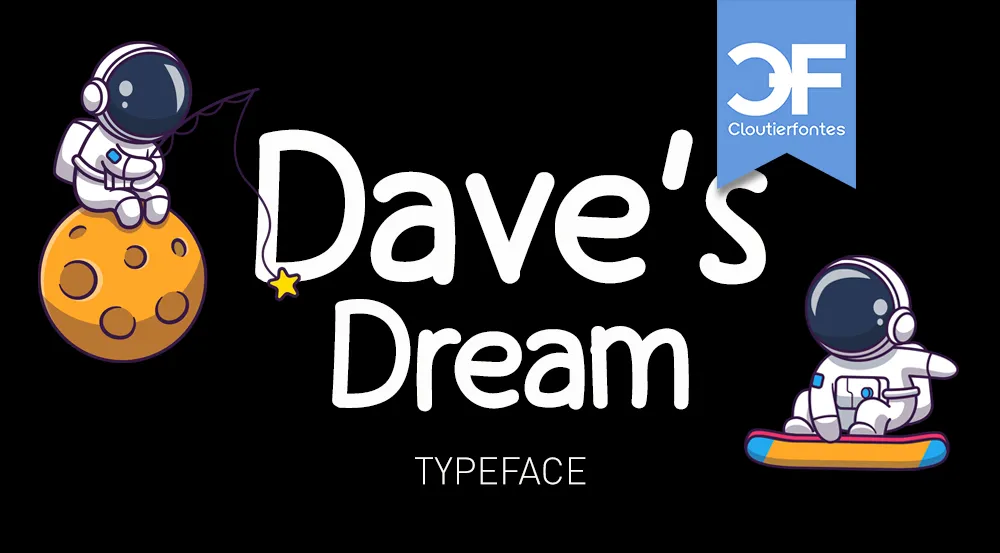
CF Dave’s Dream Font – Download Grátis
Esta é uma fonte sans-serif agradável e fina perfeita para projetos criativos de todos os tipos. Suas linhas simples e elegantes tornam-a ideal para agregar ao seu trabalho, pois ela destaca-se naturalmente entre o resto do conteúdo. Seja você um designer gráfico, um escritor, ou até mesmo um fotógrafo que busca dar mais vida a suas imagens com uma fonte única e chamativa – essa é sua solução perfeita. Amei como ela se destacava em projetos anteriores, sempre garantindo aquele toque especial no final de cada ideia. Seja qual for o seu estilo, esta fonte é definitivamente a cara dele. Não deixe de experimentar e descobrir o brilho que essa font pode trazer à sua arte gráfica!